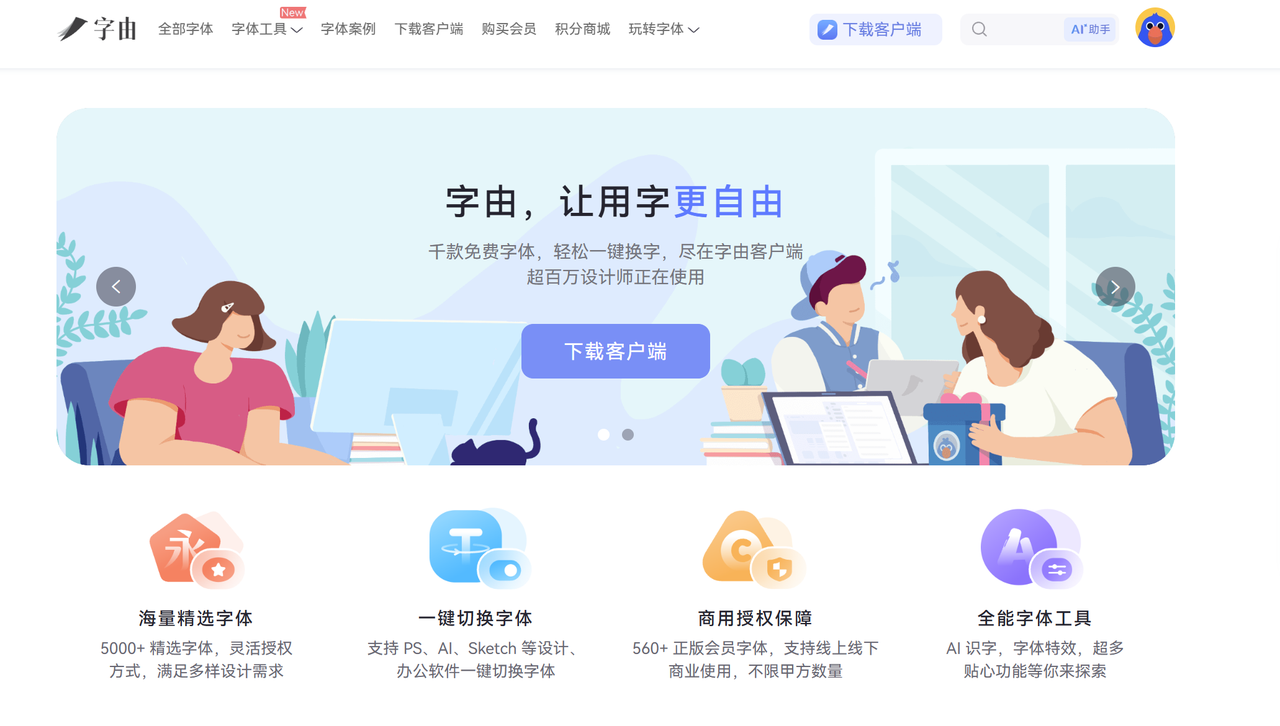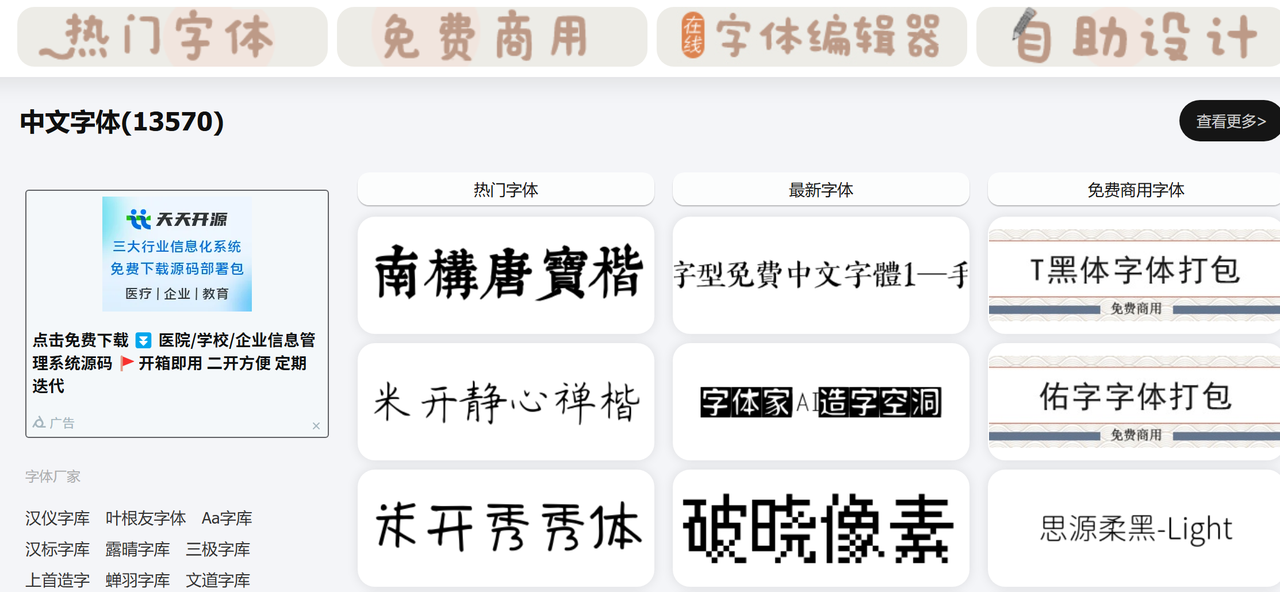
找标准隶书字体总踩雷?4个实测好用的下载网站推荐
在设计排版、书法练习、公文排版等场景中,标准隶书字体凭借庄重典雅的风格,成为很多人的首选。但实际找字体时,不少人都会陷入“踩雷循环”:要么下载到的隶书字体变形走样,根本不符合标准规范;要么网站捆绑大量垃圾软件,一不小心就中招;还有的字体标注“免费”,用了才发现涉及版权问题,后续维权麻烦不断。为了帮大家避开这些坑,从市面上20+主流字体下载网站,筛选出4个真正好用的平台,每一个都经过安全性、字体规范性、实用性的严格检验。
一、字由网:设计师首选,标准隶书一键直达
作为常年混迹设计圈的人,字由网是我私藏的字体神器,找标准隶书字体时,它也是我最先想到的平台,实测体验拉满。字由网的字体审核挺严的,隶书分类里,不管是曹全碑、乙瑛碑那种经典汉隶,还是方正隶书这种适合现代设计的标准款,都能找到。每款字体都能直接预览,不同字号、字形看得明明白白,不用像以前那样,下载完才发现是变形的“伪隶书”,白浪费时间。下载超干净,没有乱七八糟的捆绑:这点真的要夸!我试着重下了好几款隶书字体,全程没弹一个广告。
二、字体之家:新手友好,隶书字体分类清晰好查找
刚接触字体下载的朋友,选字体之家准没错。最大的感受就是“贴心”,从找字体到下载安装,每一步都替新手考虑到了。字体之家把隶书细分成了“标准隶书”“经典汉隶”“创意隶书”等多个子分类。比如你要做公文排版,直接选“标准隶书”就能找到符合规范的字体;想做国风海报,就去“创意隶书”分类找汉仪瘦金隶这类兼具风格与美感的字体,不用在海量字体里逐个筛选,效率大大提升。
三、你好字库:免费商用首选,隶书字体合规无风险
对于有商业使用需求的人来说,你好字库绝对是“宝藏网站”。实测发现,这个网站的核心亮点就是“全免费可商用”,而且收录的隶书字体质量很高,完全能满足商业设计、公文排版等场景的需求。网站上所有收录的隶书字体,都明确标注“免费可商用”,且经过严格的授权核对,来源清晰。不管是个人做海报、自媒体封面,还是企业做宣传册、产品包装,都能放心使用,再也不用为了版权问题到处查资料、找授权,彻底告别侵权风险。
四、100font:免费商用字体库,隶书字体实用又省心
100font是专注于免费商用字体的平台,它的隶书字体不仅免费好用,而且版权有保障,特别适合个人设计、中小企业商用等场景。100font的界面没有多余广告,非常清爽。搜索“隶书”后,字体列表一目了然,每款字体都有清晰的预览效果,点击字体名称进入详情页,能直接看到“立即下载”按钮,无需注册登录,一键就能获取字体安装包,操作门槛极低。
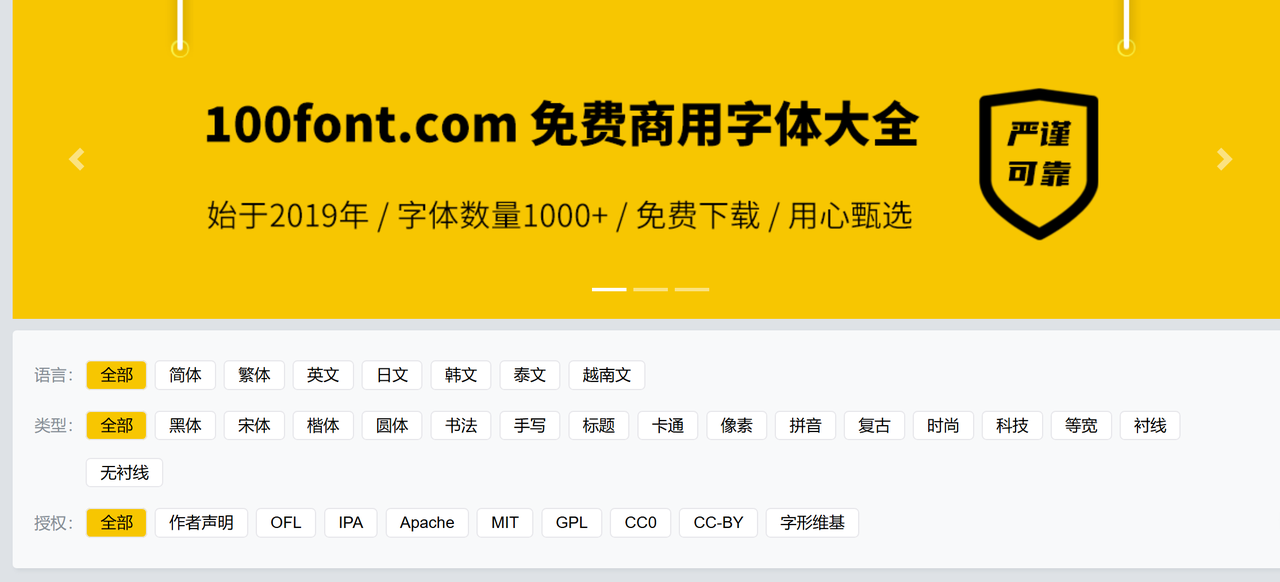
以上4个网站都是实测好用的隶书字体下载平台,各有侧重,大家可根据自己的需求选择: 设计师优先选字由网:字体全、功能全,附加的字体搭配推荐能提升设计效率;新手选字体之家:分类清晰、引导到位,下载零门槛,上手难度低;商业使用选你好字库:全部字体免费商用,版权无隐患,适合个人和企业;追求免费商用高品质100font:字体免费无版权风险,种类丰富,适合个人和中小企业的各类设计场景。